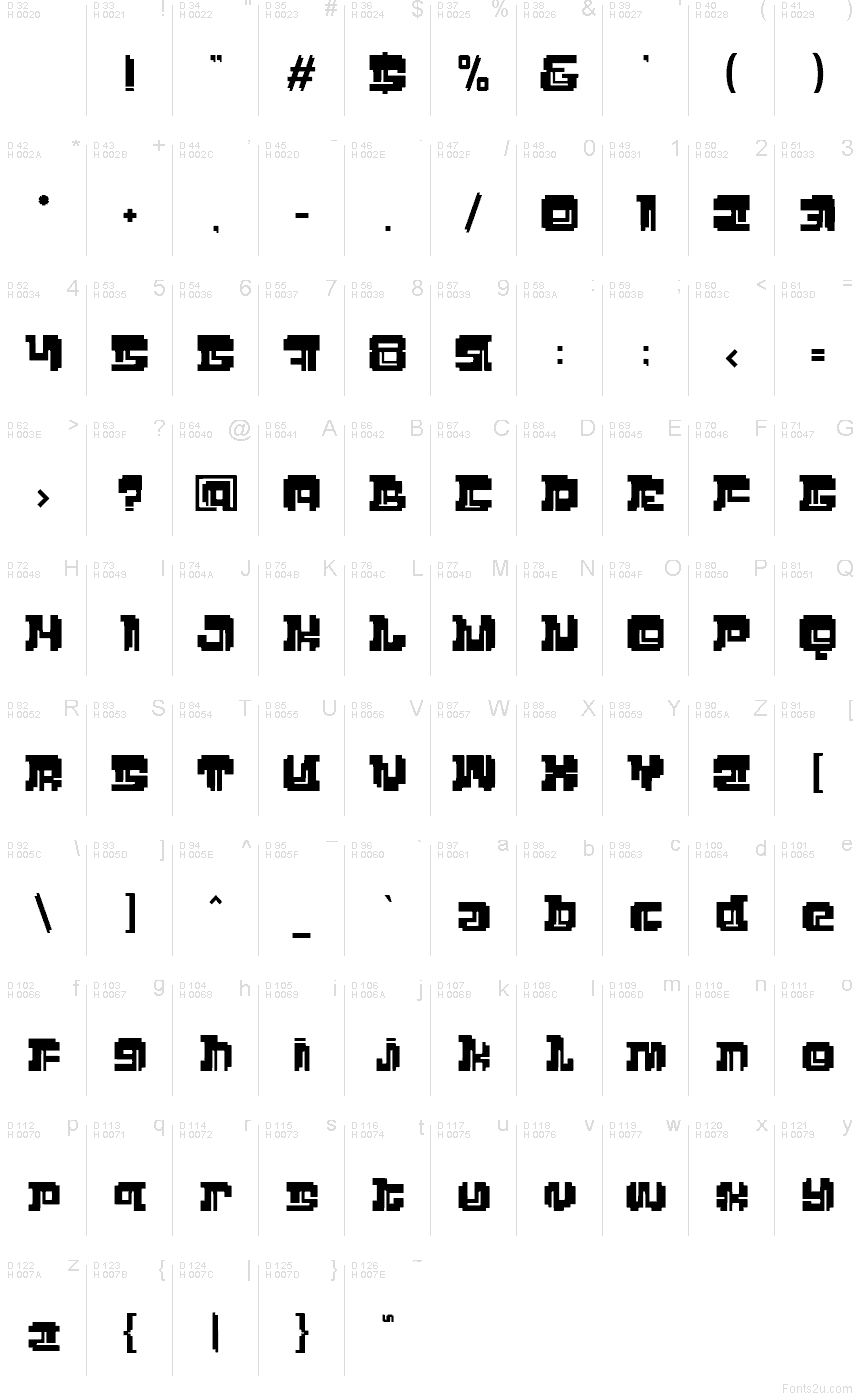
Techno Wave od Putracetol Studio je bezplatné futuristické písmo typu display, vytvořené z mohutných obdélníkových bloků a hlubokých stupňovitých výřezů, které písmenům dodávají téměř labyrintový vzhled. Opakující se vertikální členění a úzké vnitřní kanálky mu dodávají digitální rytmus připomínající tištěné spoje, což je mnohem zajímavější než běžné sci-fi fonty.
Tato struktura se skvěle hodí pro názvy her, letáky elektronické hudby, streamovací grafiku, propagační materiály aplikací a nadpisy plakátů, kde výrazná silueta písem tvoří základ layoutu. Ideálně se hodí také pro branding technologických akcí nebo miniatury na YouTube, zejména pokud chcete, aby krátká slova působila jako zakódované signály místo obyčejného geometrického písma.